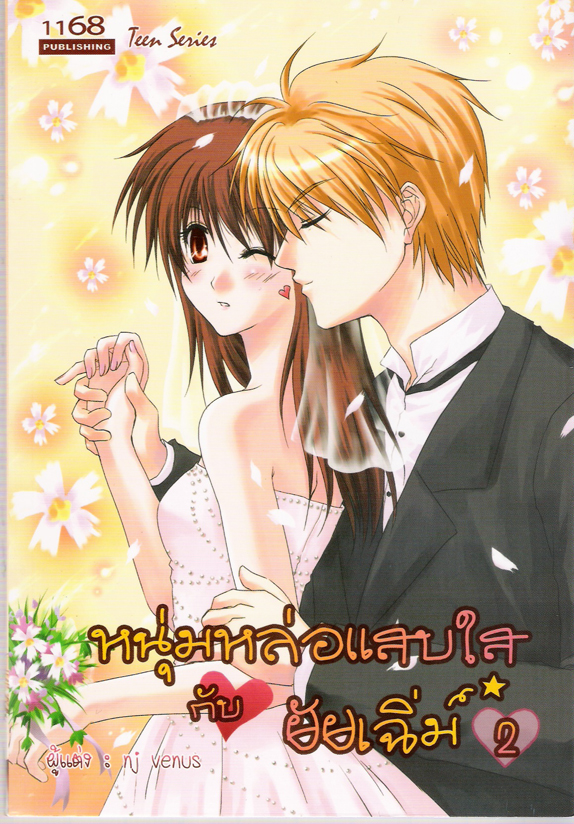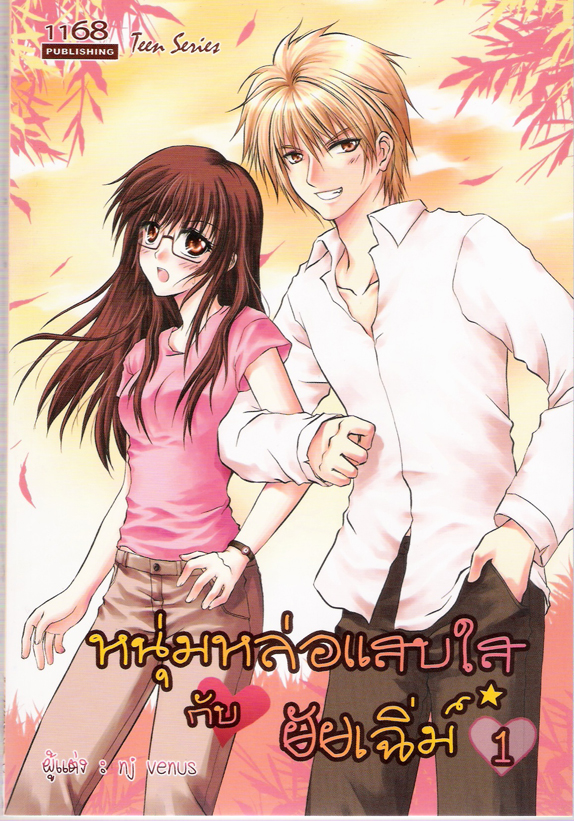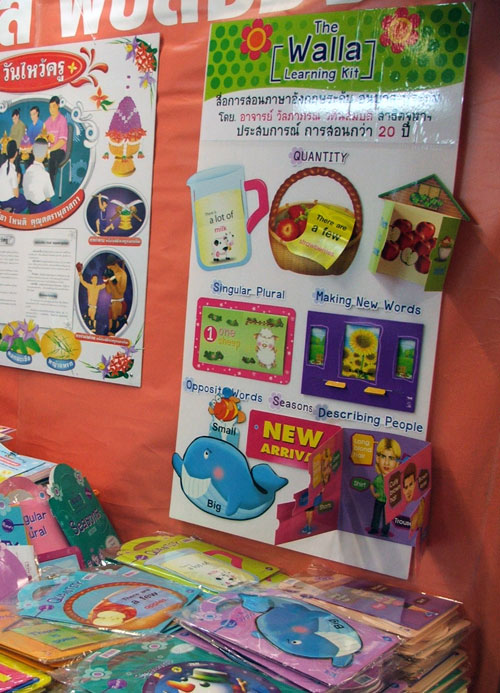
เป็นสองเล่มแรกที่ตูเห็นว่าใช้...
ไชโยดัง ๆ ให้ฟอนต์ไชโยของลุงป๋วยหน่อยครับ
ที่ใส่ภาพใหญ่เพราะดีใจมาก ๆ เลยครับ
ไชโย!!!!  :02: :02: :02:
มีฟอนต์เจ๊นุึ่นด้วยนะ  :45:
(แต่ถ้ามีแต่ฟอนต์แอน เชิญจู๋นู้นเลยครับ)
ถ้าเล่มไหนมีฟอนต์พี่แอน ผมจะไม่โพสต์
เพราะคนอื่นคงทำให้แล้ว  :39:
ถ้าจะเอือืมตู เอือมฟ๐นต์ป้าคนนี้ก่อนดีกว่าครับ
เจอทุกงาน เห็นทุกงาน  :07:
(จริงๆ แล้วไม่ชอบ ก ไก่ของฟ๐นต์นี้เลยแฮะ มีบางคนเอาไปทำในงานแล้วแก้เฉพาะตัว ก เป็นอีกฟ๐นต์)
อุ๊ย แม่ร่วง  :40:
เดี๋ยวปั๊ดตัดภาพข้างล่างไปไว้อีกจู๋หรอก  :07:
รู้จักกิฟฟารีนมั้ย [บริษัทขายตรงหลายชั้น]
พอดีไปเจอมาในนิตยสาร "เส้นขอบฟ้า" เล่มครบรอบ 10 ปีบริษัท
นับว่าเป็นเกียรติมาก ทั้งๆที่เนื้อหาเกือบทั้งเล่ม ใช้กิตติธาดา
แต่หน้าปกกับใช้ฟอนต์ผม
ขอบคุณมากครับ (เอามาโพสเองน่ะ จะมีปัญหามั้ย)
หน้าด้านจริงๆ
โปรโมตฟ๐นต์ตัวเองไม่ลืมหูลืมตา
แต่เฮียเป็นคนเริ่มวัฒนธรรมนี้เองนะครับ  :26:
ไปเห็นจั่วหัวมาแล้ว ช่องไฟอุบาทว์ชาติชั่วมากครับ
เดี๋ยวออกเวอร์ชั่นแก้ พร้อมเวอร์ชั่นตัวบางด้วยดีกว่าเนาะ  :12:
เว็บนี้ก็ใช้ครับ http://www.facthosting.com  :42:
เอ้า ก็ใช้จริงๆ นี่ ไม่ได้โม้  :40: